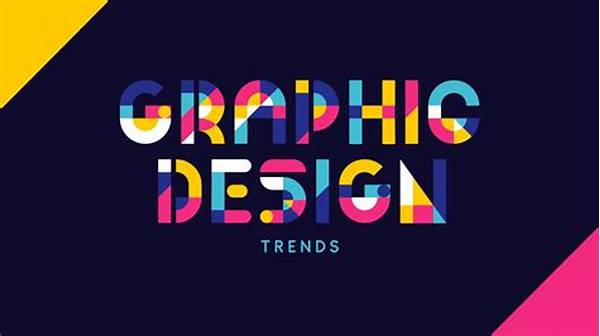
Hai, pembaca setia! Apakah kalian pernah memperhatikan bagaimana tampilan huruf-huruf di layar ponsel atau komputer kalian? Itulah salah satu hasil dari tren desain font modern yang sedang berkembang. Desain font tidak hanya tentang bagaimana huruf terlihat, tetapi juga bagaimana perasaan yang mereka sampaikan. Mari kita eksplor lebih dalam apa yang menjadi tren dalam dunia tipografi saat ini!
Kembali ke Dasar
Dalam beberapa tahun terakhir, ada kecenderungan untuk kembali ke desain yang lebih minimalis dan sederhana. Para desainer tampaknya ingin menonjolkan keindahan dalam kesederhanaan. Tren desain font modern ini menekankan pada garis-garis bersih dan bentuk dasar yang mudah dibaca. Font sans-serif, seperti Helvetica atau Arial, kembali menjadi bintang karena fungsionalitas dan kejelasan yang ditawarkannya. Namun, tentu saja, kembali ke dasar bukan berarti membosankan. Dalam konteks yang tepat, desain font sederhana bisa menjadi sangat kuat dan efektif. Dengan cara ini, tren desain font modern dapat membuat komunikasi visual menjadi lebih jelas dan langsung, memberikan pengalaman yang menyenangkan bagi pembaca.
Selain itu, tren desain font modern juga menyoroti pentingnya tipografi yang dapat diakses oleh semua orang, termasuk mereka yang memiliki gangguan penglihatan. Font yang sederhana dan bersih membantu memudahkan semua orang dalam membaca dan menikmati konten, menjadikannya lebih inklusif. Ini adalah contoh bagaimana estetika dan etika dapat berpadu dengan baik dalam desain. Terlepas dari minimalisme, variasi gaya dan berat font tetap memberikan ruang bagi kreativitas desainer dalam membuat pekerjaan mereka unik dan berkesan. Dalam konteks ini, tren desain font modern tidak hanya mementingkan penampilan, tetapi juga fungsionalitas secara keseluruhan.
Eksplorasi Warna
Desain font modern juga berani bermain dengan warna. Tidak hanya hitam dan putih, desainer kini menggunakan palet warna yang lebih berani. Tren desain font modern ini mengajak kita untuk berani keluar dari zona nyaman dan mengeksplorasi penggunaan warna dalam tipografi. Warna dapat menambah dimensi baru dalam desain, dan jika digunakan dengan bijak, dapat mempengaruhi bagaimana audiens memproses informasi.
1. Penggunaan gradien warna mulai populer untuk memberikan efek kedalaman pada huruf.
2. Perpaduan warna neon membuat desain lebih menonjol, terutama dalam desain digital.
3. Efek warna-warni juga sering dipakai dalam kampanye yang ditujukan untuk audiens muda.
4. Warna kontras yang cerah memberikan efek dramatis yang memikat mata.
5. Ada juga tren desain font modern yang mengadopsi warna-warna pastel untuk tampilan yang lebih lembut.
Tipografi Animasi
Saat ini, tipografi tidak hanya statis. Tren desain font modern juga mencakup penggunaan animasi dalam font. Misalnya, saat kita mengarahkan kursor pada teks, huruf-huruf itu bisa bergerak atau berubah warna. Ini memberikan pengalaman interaktif yang menarik bagi audiens. Menambahkan animasi pada tipografi dapat menghidupkan desain dan membuatnya lebih dinamis. Selain itu, tipografi animasi memungkinkan desainer untuk menyampaikan pesan dengan cara yang lebih menarik dan tak terlupakan.
Bayangkan sebuah judul yang secara perlahan bergerak masuk ke layar atau menjadi lebih besar saat kita menggulir ke bawah. Efek-efek ini tidak hanya menarik perhatian, tetapi juga menambah dimensi lain dalam mendesain. Tren desain font modern ini memberi desainer kesempatan untuk bermain dengan waktu dan gerakan dalam karya mereka. Namun, penting untuk diingat bahwa keberhasilan animasi tipografi tergantung pada kemampuannya untuk meningkatkan, bukan mengganggu, pesan utama dari desain.
Variabilitas dan Fleksibilitas
Salah satu terobosan dalam tren desain font modern adalah font variabel. Font jenis ini memungkinkan desainer untuk membuat modifikasi yang lebih besar pada ketebalan, lebar, dan tinggi huruf dalam satu file font. Dengan font variabel, kita tidak lagi membutuhkan banyak file font untuk gaya atau berat huruf yang berbeda. Ini adalah kemajuan yang sangat membantu dalam proses desain dan meningkatkan efisiensi kerja desainer. Selain itu, fleksibilitas ini membuka lebih banyak kemungkinan kreatif dalam mendesain.
Menggunakan font variabel adalah seperti memiliki seluruh keluarga font di ujung jari Anda, semuanya dapat disesuaikan sesuai kebutuhan spesifik proyek Anda. Ini juga memungkinkan pengoptimalan yang lebih baik untuk penggunaan di perangkat yang berbeda. Tren desain font modern ini merayakan fleksibilitas dan adaptabilitas dalam mendesain, mencerminkan lingkungan digital yang selalu berubah. Dengan demikian, para desainer dapat dengan mudah menyesuaikan tampilan tipografi dengan konteks media dan audiens.
Sentuhan Vintage dalam Desain Modern
Menggabungkan unsur-unsur vintage dengan gaya modern telah menjadi bagian dari tren desain font modern. Font dengan sedikit sentuhan klasik atau retro dapat membawa nostalgia dan emosi tertentu ke dalam desain. Ini adalah teknik yang efektif, terutama jika disesuaikan dengan konteks yang tepat. Dalam dunia yang semakin digital, elemen klasik ini memberikan rasa koneksi dengan masa lalu, memberikan keseimbangan yang baik antara lama dan baru.
Dengan menambahkan elemen vintage, desain dapat memiliki nuansa yang lebih hangat dan akrab. Meskipun terlihat kuno, ketika digabungkan dengan tren desain font modern, hasilnya bisa sangat kontemporer dan segar. Sentuhan ini menciptakan daya tarik estetika yang bisa menonjol dalam lautan desain digital masa kini. Tren ini menunjukkan bagaimana kreativitas dan inovasi bisa datang dari menggabungkan elemen-elemen yang tampaknya berlawanan.
Dengan berbagai inovasi seperti font variabel dan desain responsif, desainer mendapatkan kebebasan lebih banyak untuk mengekspresikan ide-ide kreatif mereka. Di sisi lain, tren ini juga menantang para desainer untuk terus berpikir ke depan dan beradaptasi dengan perkembangan teknologi. Tren desain font modern memang menawarkan lebih banyak pilihan dan peluang untuk berinteraksi dengan audiens, menjadikannya salah satu elemen penting dalam dunia desain grafis. Apakah Anda siap menjelajahi lebih dalam dunia tipografi modern?